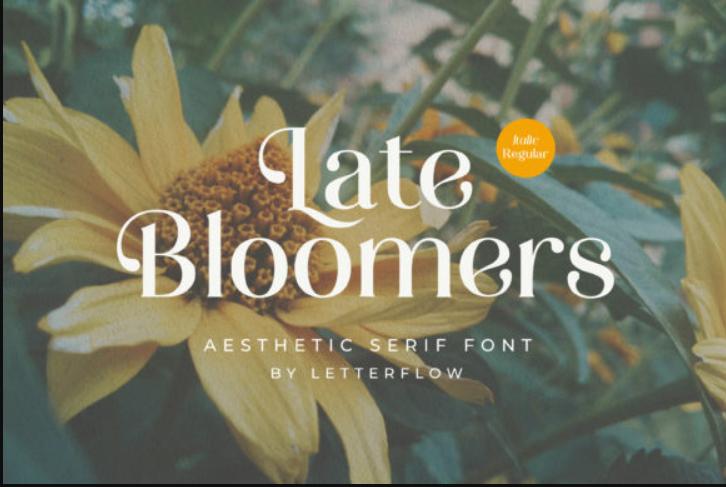
Late Bloomers - это элегантный и отчетливый шрифт с засечками. Он имеет стильный, элегантный и современный вид, который можно использовать для логотипов, брендинга, приглашений, канцелярских принадлежностей, свадебного дизайна, сообщений в социальных сетях.